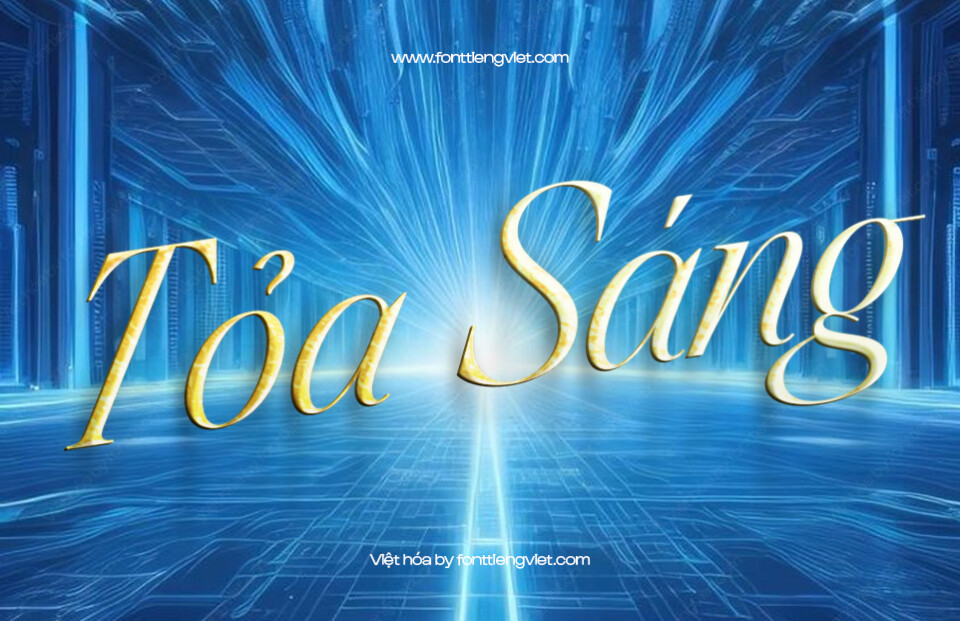
Font Việt hóa 1FTV VIP Griffiths
Font Việt hóa 1FTV VIP Griffiths – Bộ font thiết kế đẳng cấp và hiện đại dành cho nhà trường
Giới thiệu về Font Việt hóa 1FTV VIP Griffiths và ứng dụng thực tế
Trong thế giới thiết kế đồ họa hiện nay, việc lựa chọn một Font Miễn Phí chất lượng luôn là ưu tiên hàng đầu của các bạn học sinh và giáo viên. Font Việt hóa 1FTV VIP Griffiths nổi lên như một giải pháp hoàn hảo, mang lại vẻ đẹp tinh tế và chuyên nghiệp cho mọi bản thiết kế. Đây là bộ phông chữ được tinh chỉnh kỹ lưỡng về dấu tiếng Việt, giúp người dùng không còn lo lắng về lỗi hiển thị khi soạn thảo văn bản hay làm slide bài giảng. Với đường nét thanh thoát nhưng không kém phần mạnh mẽ, bộ font này phù hợp cho cả tiêu đề lẫn nội dung chi tiết. Việc sử dụng Font Việt hóa 1FTV VIP Griffiths sẽ giúp các dự án sáng tạo tại trường học trở nên đồng nhất và bắt mắt hơn bao giờ hết.
Tại sao nên chọn Font Việt hóa 1FTV VIP Griffiths cho giáo dục?
Môi trường giáo dục luôn cần những yếu tố trực quan rõ ràng để truyền tải kiến thức hiệu quả. Font Việt hóa 1FTV VIP Griffiths đáp ứng tốt tiêu chí này nhờ khả năng đọc hiểu cao và phong cách hiện đại. Khi các em học sinh thực hiện báo cáo hay làm tập san, bộ font này giúp tạo điểm nhấn sang trọng mà vẫn giữ được sự gần gũi. Đối với các thầy cô, việc sử dụng một bộ font chuẩn Việt hóa giúp tiết kiệm thời gian chỉnh sửa lỗi font chữ vốn rất phổ biến ở các bộ phông nước ngoài. Hơn nữa, tính linh hoạt của nó cho phép ứng dụng từ in ấn poster sự kiện trường học cho đến thiết kế giao diện ứng dụng học tập trực tuyến.
Đặc điểm nổi bật của Font Việt hóa 1FTV VIP Griffiths trong thiết kế
Một trong những điểm khiến Font Việt hóa 1FTV VIP Griffiths trở nên khác biệt chính là cấu trúc các ký tự được sắp xếp rất hài hòa. Bộ font bao gồm nhiều kiểu dáng từ mảnh đến đậm, giúp người dùng dễ dàng phân cấp thông tin trong một trang văn bản. Điều này cực kỳ quan trọng trong việc trình bày các đề án nghiên cứu hoặc các bài thuyết trình chuyên sâu tại trường học. Font Việt hóa 1FTV VIP Griffiths không chỉ đơn thuần là các con chữ, mà nó còn mang giá trị thẩm mỹ cao, khơi nguồn cảm hứng sáng tạo cho thế hệ trẻ đam mê mỹ thuật số.
Cách tối ưu hóa Font Việt hóa 1FTV VIP Griffiths trên các phần mềm
Lời kết và định hướng sử dụng Font Việt hóa 1FTV VIP Griffiths hiệu quả
Việc sở hữu một bộ font chữ đẹp như Font Việt hóa 1FTV VIP Griffiths sẽ giúp nâng tầm giá trị cho các sản phẩm trí tuệ của bạn. Đây chắc chắn là công cụ không thể thiếu trong kho tài nguyên của những người yêu thích thiết kế tại Việt Nam. Hy vọng rằng qua bài viết này, các bạn đã hiểu rõ hơn về tính năng và ưu điểm của bộ font đặc biệt này. Hãy bắt đầu trải nghiệm ngay hôm nay để thấy được sự khác biệt trong từng khung hình và trang viết. Để tìm kiếm thêm các tài nguyên thiết kế chất lượng, bạn có thể tham khảo tại Font Miễn Phí, Font Việt Hóa, Font Việt hóa 1FTV VIP Griffiths để luôn cập nhật những xu hướng mới nhất cho dự án của mình.